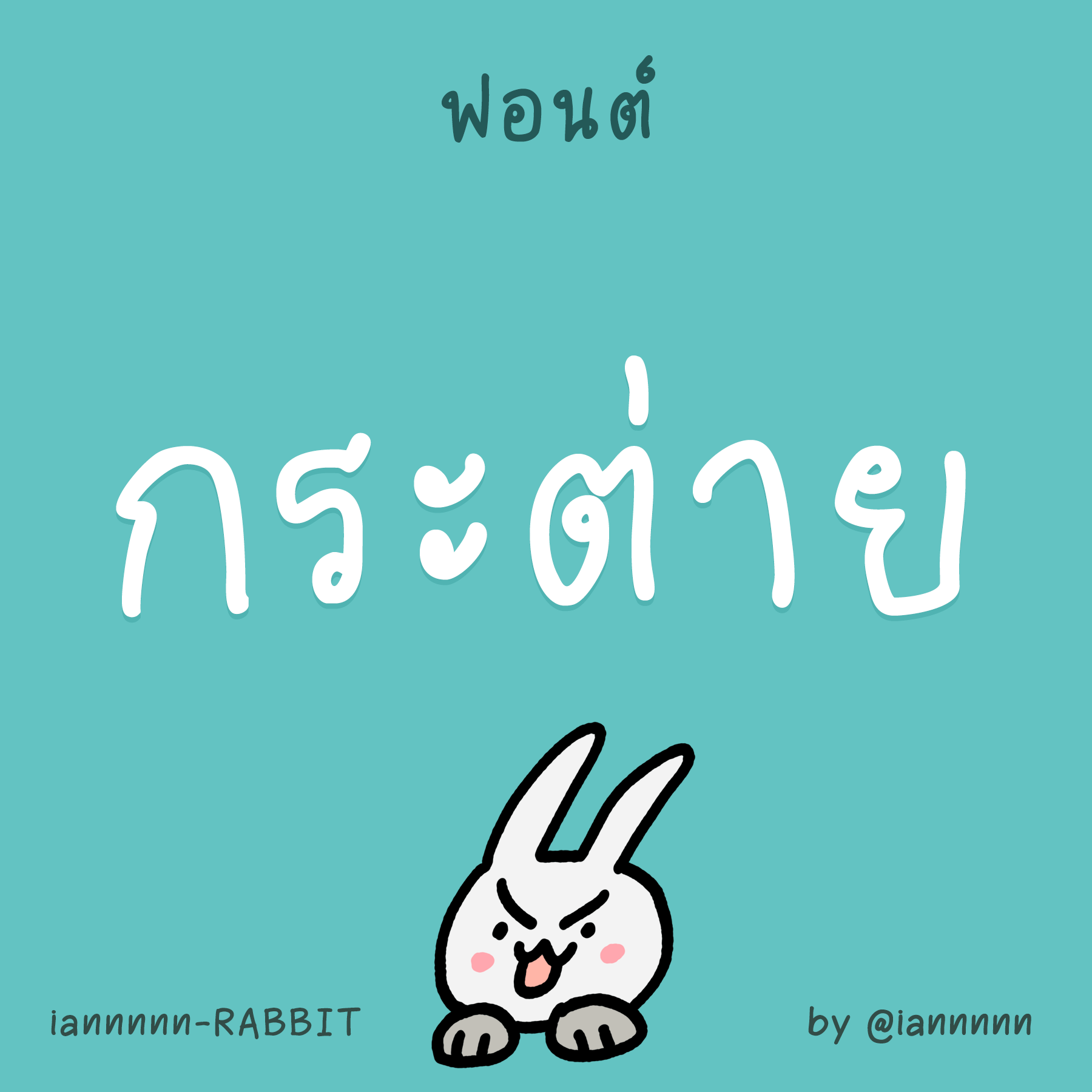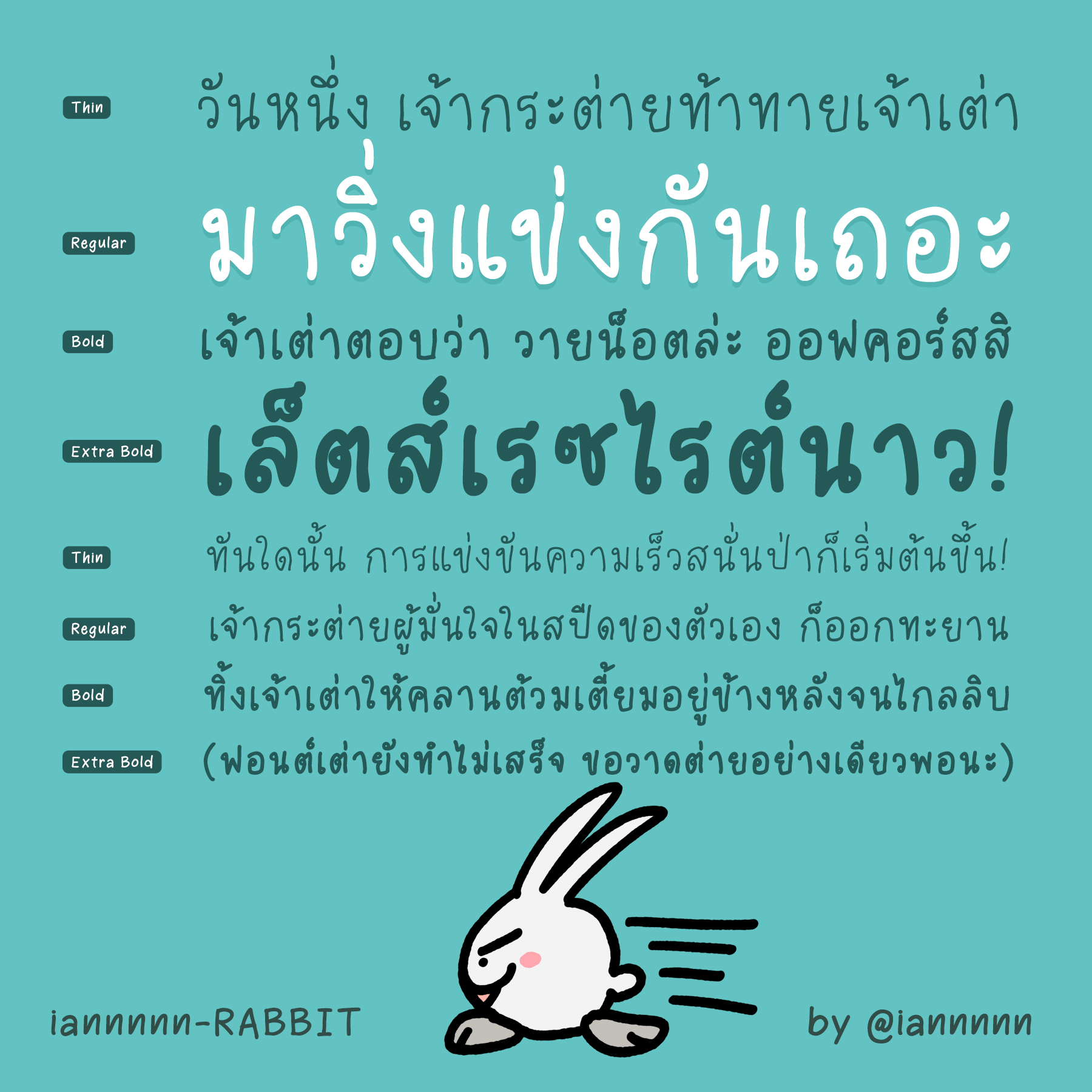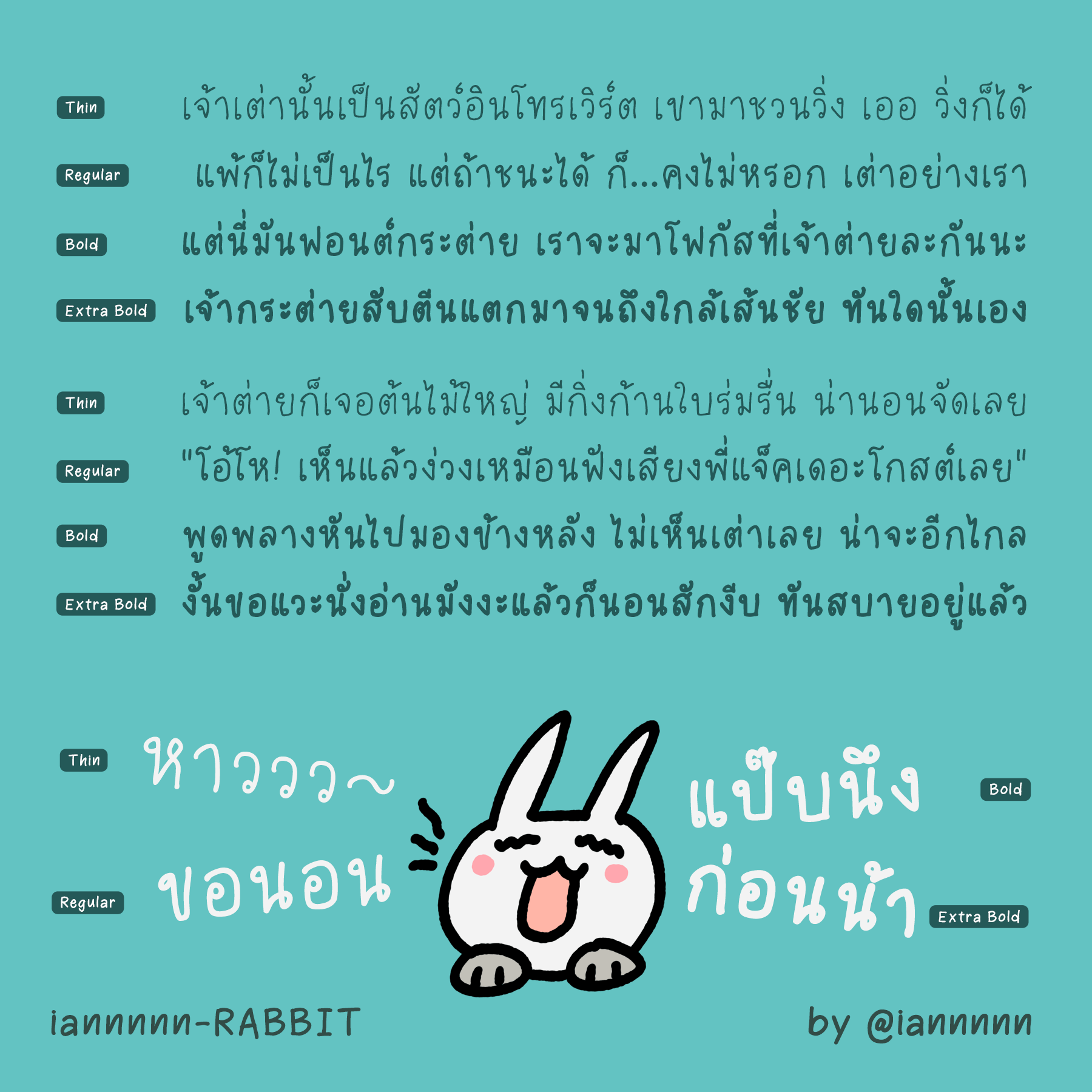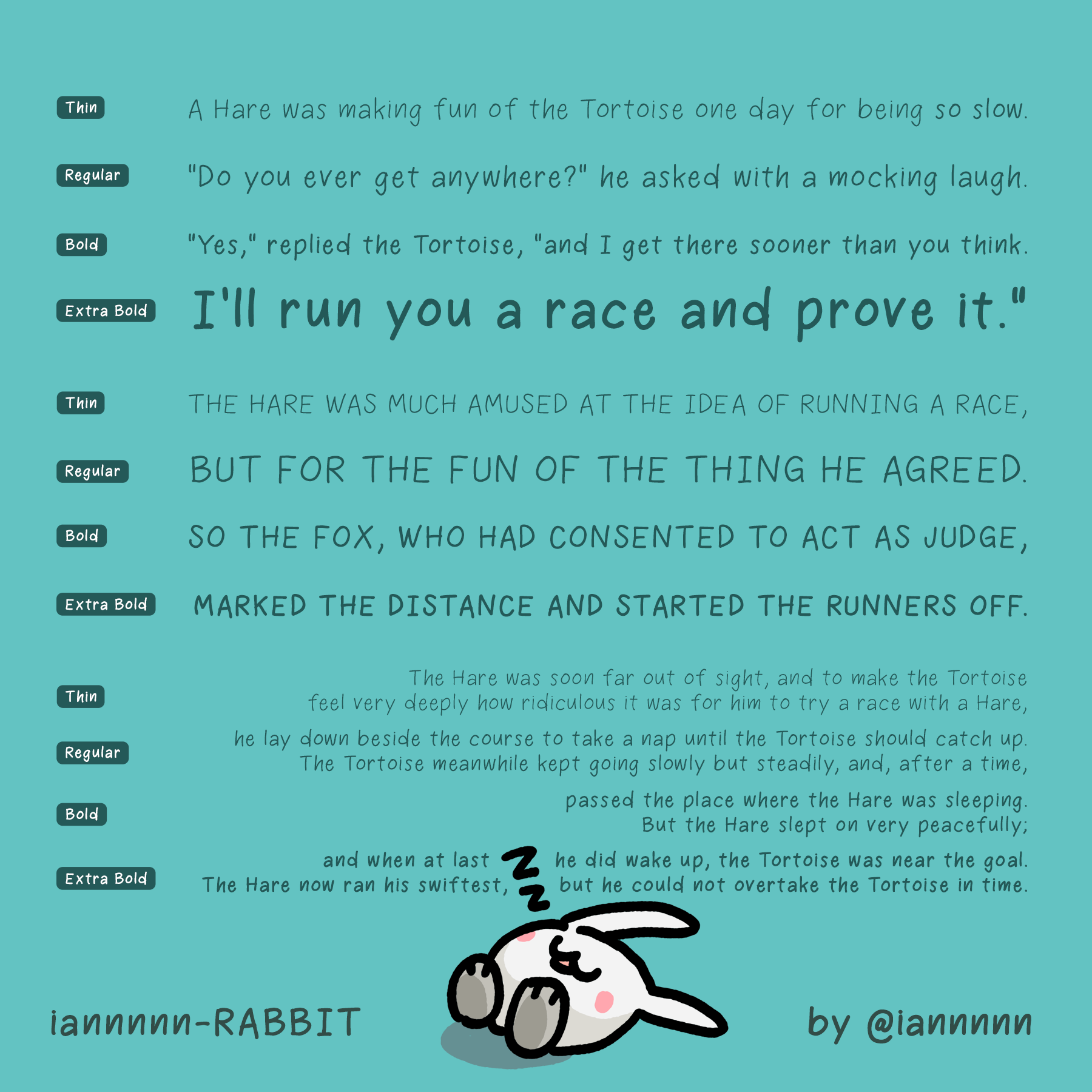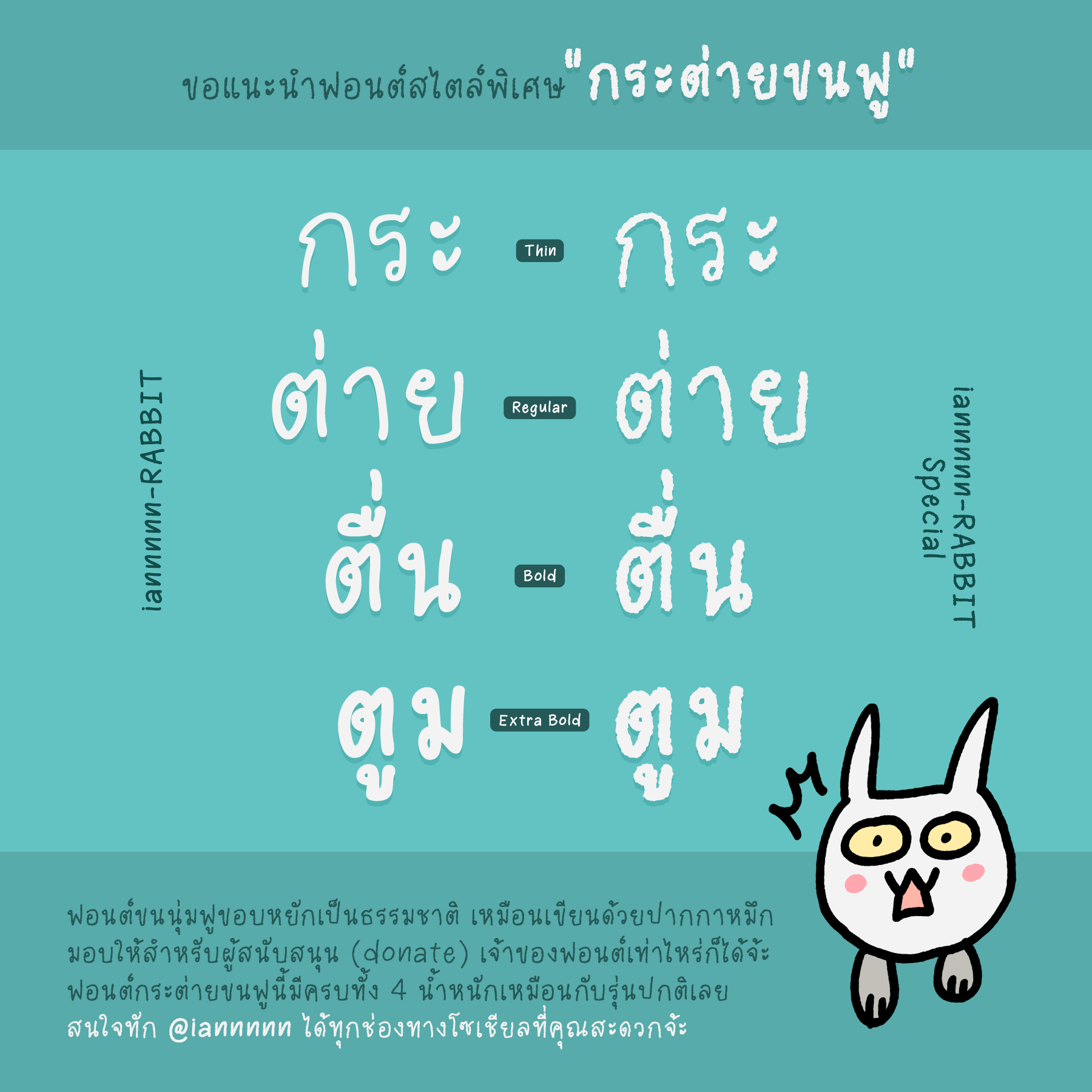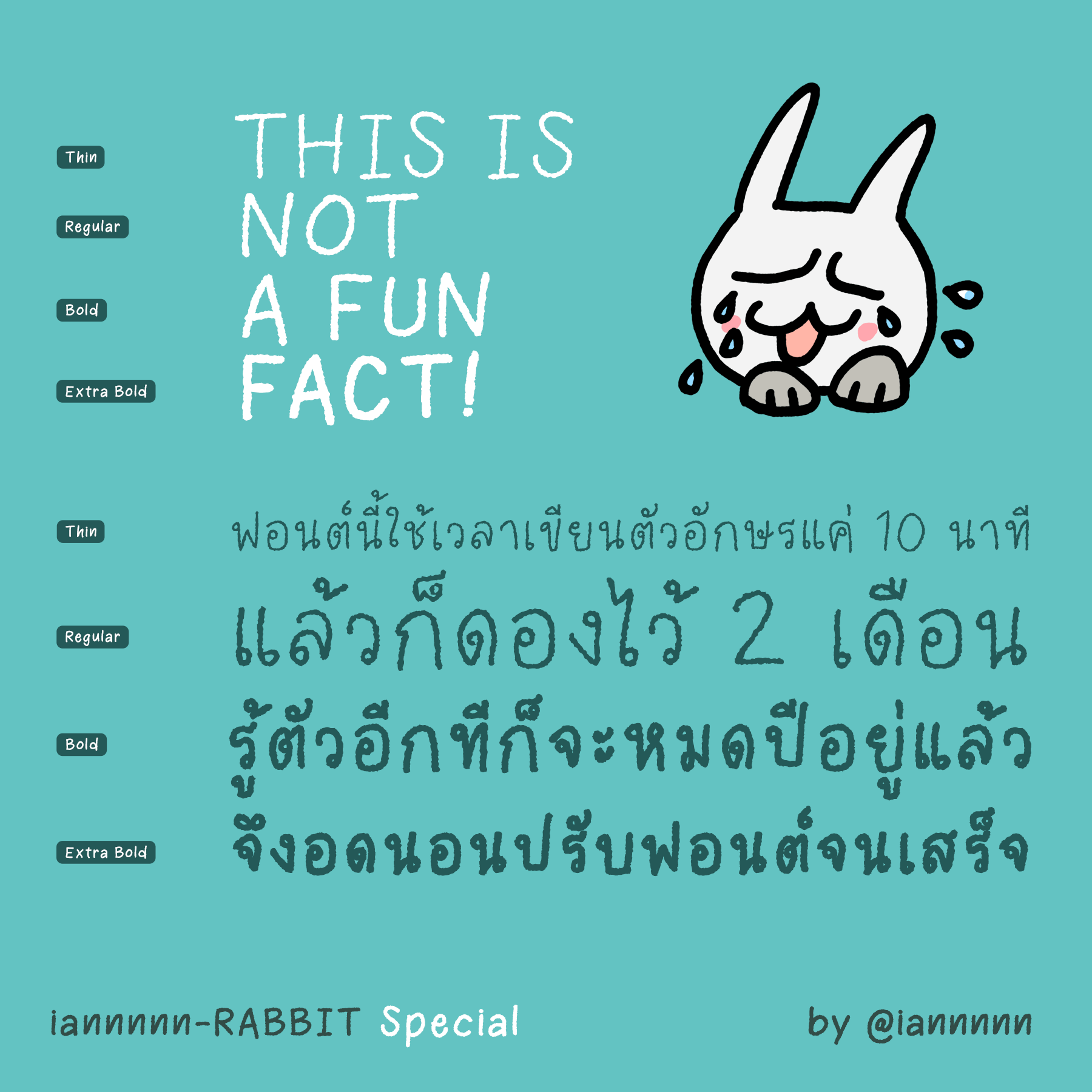
กระต่าย (iannnnn-RABBIT)
ลองเขียนในมือถือ แป๊บเดียวก็เสร็จ พอเห็นว่ามันทำเร็วเลยชะล่าใจ ดองไว้ 2 เดือน มาล่กทำให้เสร็จเอาตอนสิ้นปี ชะตากรรมเหมือนกระต่ายกับเต่าเลย T___T ฟอนต์มี 4 น้ำหนัก ทั้งบาง กลาง หนา และหนัก (พร้อมสไตล์ขนฟูอีก 4 น้ำหนักสำหรับผู้ donate เท่าไหร่ก็ได้จ้า)
ฟอนต์กระต่าย เป็นสัตว์ตัวล่าสุดที่นึกขึ้นได้ตอนที่ลองใช้แอปที่โหลดมามั่วๆ (พฤติกรรมเสี่ยง กรุณาอย่าเลียนแบบ) ปรากฏว่าแอปมันใช้ง่ายดี เลยลองเขียนตัวอักษรเป็นลายมือตัวเองเวอร์ชันมีหัว และใส่ช่องไฟกว้างนิดนึง จะได้อ่านง่ายๆ หายใจหายคอสะดวก
เขียนไปเขียนมา ทั้งไทย-อังกฤษ-ตัวเลข-สัญลักษณ์ต่างๆ จนครบ เฮ้ย 10 นาทีเสร็จ ทำไมมันง่ายงี้ เข้าใจแล้วว่าทำไมน้องๆ ในเว็บฟอนต์เขาทำกันเร็วจัง อยากได้ไอแพดเลย จะได้เร็วกว่านี้อีก 5555555 งั้นเดี๋ยวปรับช่องไฟและสระวรรณยุกต์ต่างๆ เสร็จแล้วปล่อยเลยดีกว่าๆๆๆ เย้ๆๆๆ
…ซึ่งนั่นคือความคิดเมื่อ 2 เดือนก่อนครับ
ผมมัวแต่ชะล่าใจ ใช้คำนี้นี่ถูกเป๊ะเลย มัวไปทำอย่างอื่นอยู่พักใหญ่ (รวมถึงออกแบบเว็บฟอนต์ใหม่ด้วย 5555 ทันสมัยกับเขาซะที) กว่าจะรู้ว่าดองไว้นานจนกระต่ายกลายเป็นกระต่ายหลับจนเต่าแซง ก็ถึงเดือนธันวาคมแล้ว
เฮ้ยๆๆๆๆ งั้นเลยรีบปั่นจนเสร็จ เสร็จแล้วก็ตรวจ ตรวจแล้วก็ปรับ ปรับแล้วก็ปรับอีก จนนอนดึกติดต่อกันหลายวัน นี่คือข้อเสียของคนที่เริ่มแก่ครับ มันปล่อยให้เกิดข้อผิดพลาดเล็กๆ น้อยๆ เหมือนสมัยก่อนไม่ได้จริงๆ
สุดท้าย ผ่านมาอีก 1 สัปดาห์ ฟอนต์นี้ก็เสร็จทั้ง 4 น้ำหนักเป็นที่เรียบร้อย โหลดไปใช้งานได้ตามสบายเลยครับ
เบื้องหลังการออกแบบ : ฟอนต์กระต่าย (iannnnn-RABBIT)
ฟอนต์กระต่าย (iannnnn-RABBIT)